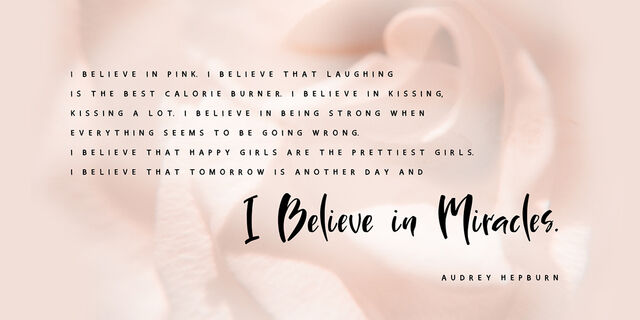
Это дополнительный шрифт без засечек из шрифтовой пары Sister Pamella Font Duo Cyrillic которая в сочетании идеально подходит для использования во всех ваших дизайнерских проектах, будь то логотипы, подписи, этикетки, дизайн упаковки, заголовки блогов. Кроме того, он будет отлично смотреться на кружках, вывесках, открытках, типографических плакатах, свадебных канцелярских принадлежностях и многом другом. Гротеск Sister Pamella Sans состоит только из прописных букв, цифр и знаков препинания и создает идеальный контраст со шрифтом Sister Pamella script. Многоязычная поддержка 31 языка на основе латиницы и кириллицы.
Шрифт разработала Ирина Двилюк в 2021 году.